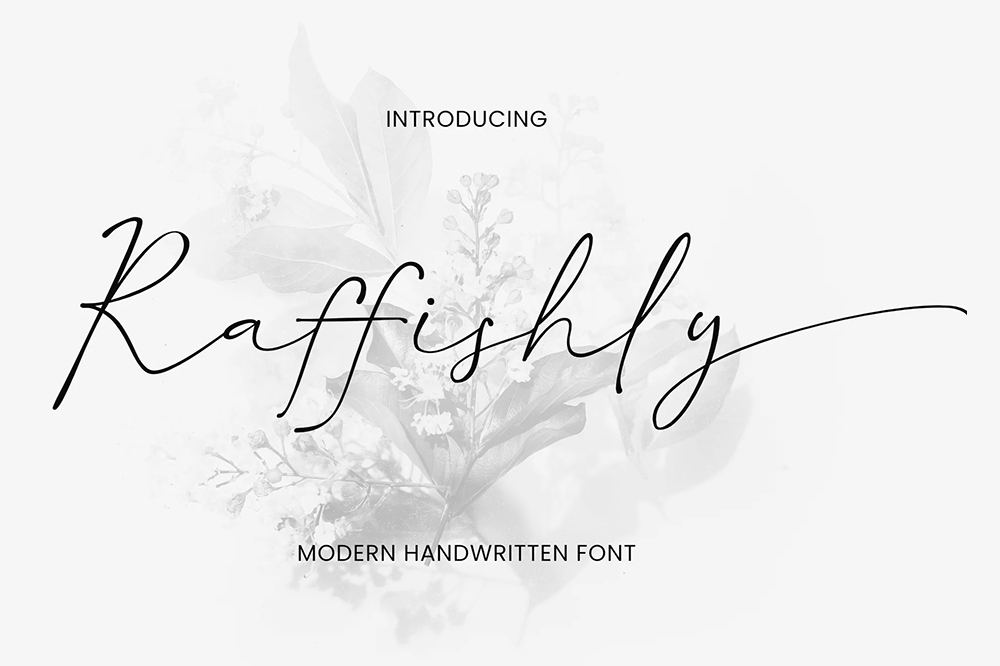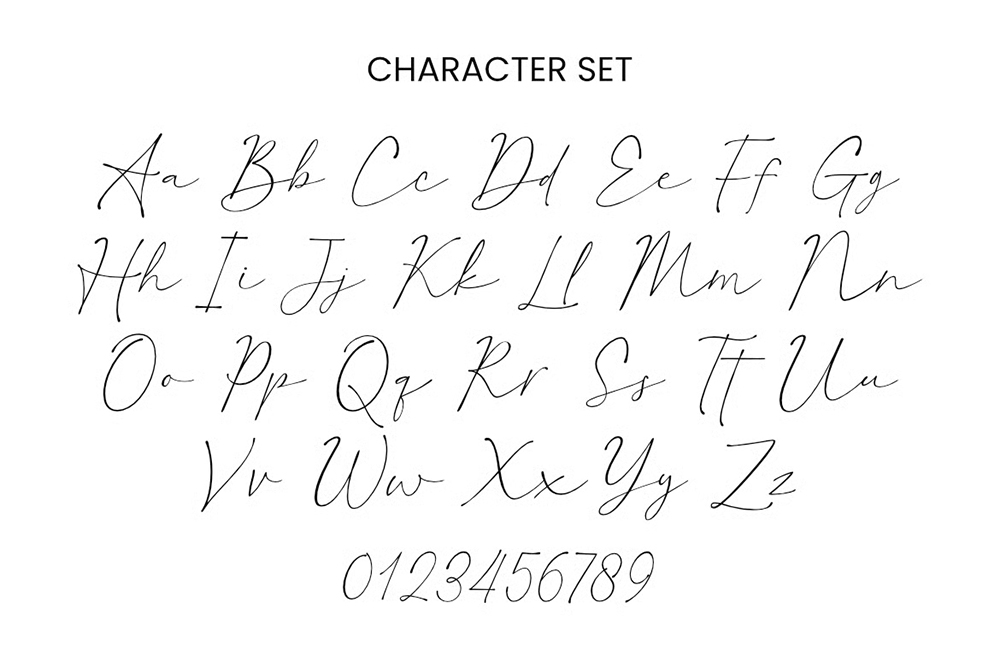
دانلود فونت انگلیسی Raffishly Font
فونت پرمیوم و انگلیسی Raffishly Font یک فونت دستنویس مدرن و لوکس است که با نوارهای دستنویس ارائه میشود. Raffishly ظاهری طبیعی دارد و در عین حال حس راحتی و ظرافت را القا میکند.
مزایای استفاده از فونت لاتین Raffishly چیست؟